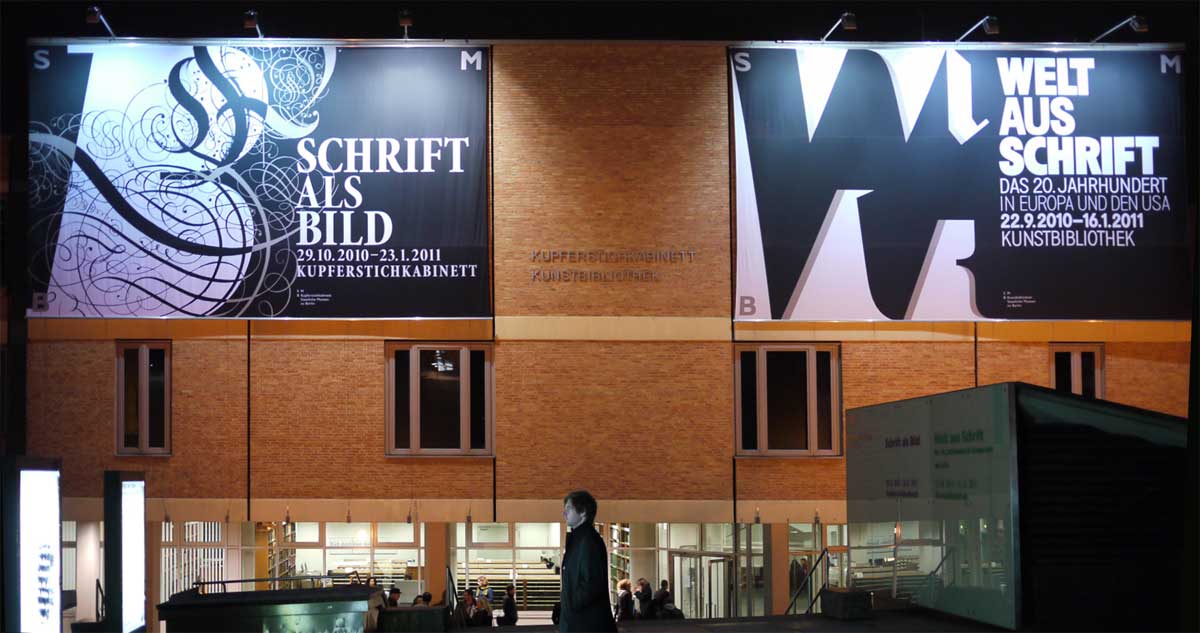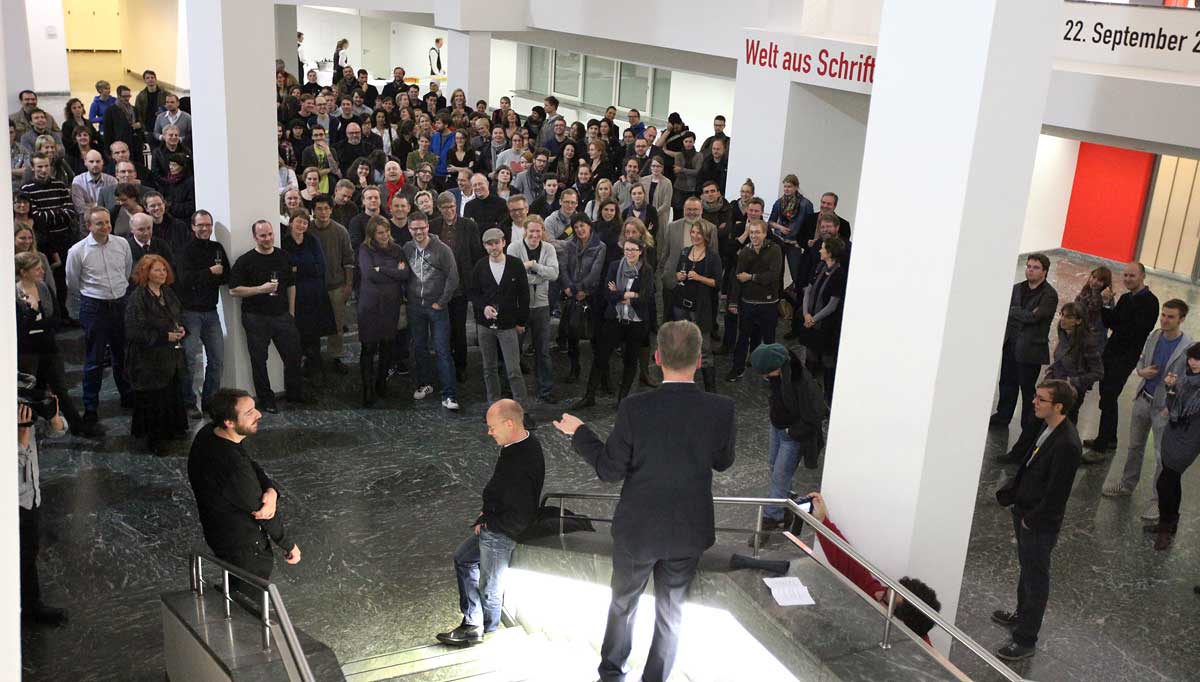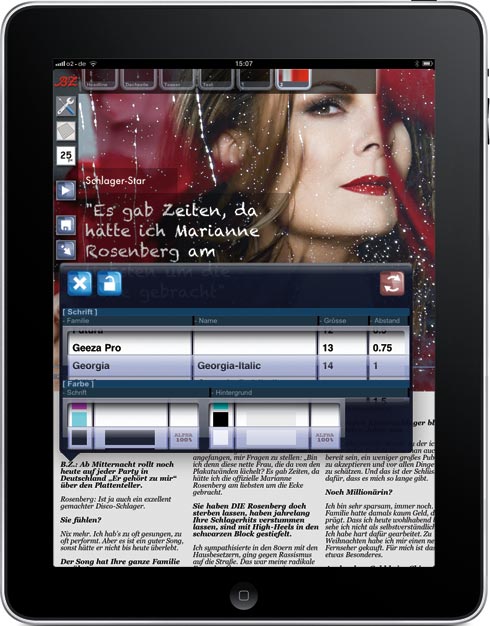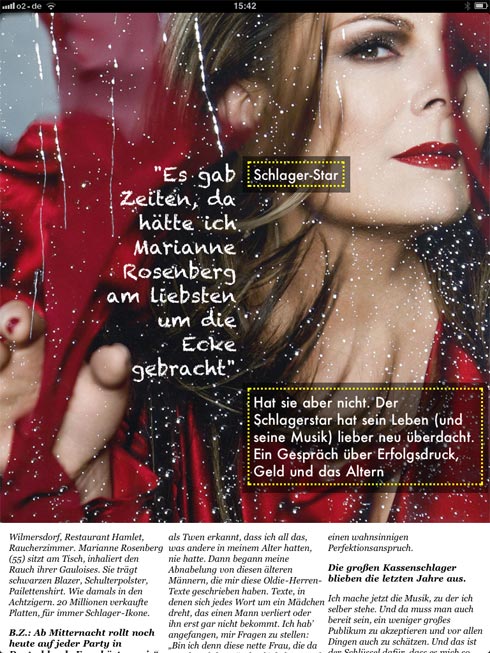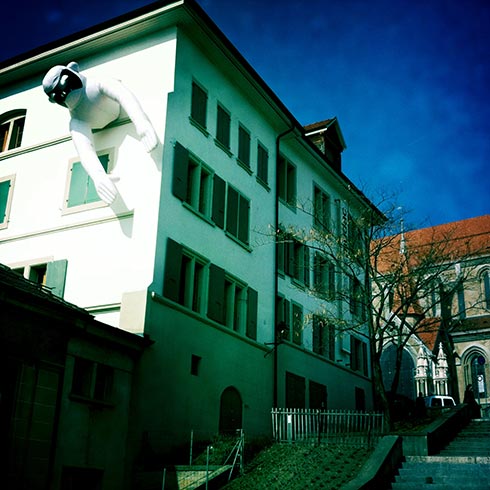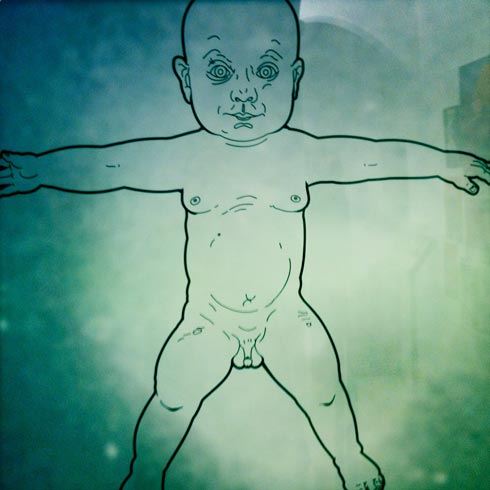
Seit 15 Jahren arbeitet der holländische Designer Diederik Corvers, Sprecher auf der TYPO Berlin 2010, mit Schrift und Typografie. In seinen kommerziellen und freien Arbeiten spielt die Textbehandlung stets eine zentrale Rolle. Corvers setzt meist eigene Fonts ein. Er produziert Bücher, Poster und CIs für verschiedene Auftraggeber in der Kulturszene. Seine autonomen Projekte finden sich im öffentlichen Raum, also da, wo Größe eher in Metern als in Punkt gemessen wird.
Heute schreibt er mir, dass seine wichtigste Schöpfung, die Schriftfamilie Ogentroost kurz vor der Fertigstellung steht. In einem reichlich bebilderten Interview mit der belgischen Designerin Veerle Pieters (Veerle’s Blog) erläutert er, warum die Arbeit an der Familie aufwändig war und so lange gedauert hat. Ein interessanter Blick hinter die Kulissen einer Schriftschöpfung: Ogentroost typeface
Im Zentrum von Lausanne, zu Füßen der Kathedrale Notre-Dame, liegt das angesagte Museum für Design und angewandte zeitgenössische Kunst, abgekürzt Mudac. Es versteht sich als Brückenbauer zwischen Kunstformen, die im traditionellen Verständnis etwas weiter auseinander liegen. Nirgendwo anders scheint eine Stefan-Sagmeister-Ausstellung besser hinzupassen, als an diesen Ort. Heute Abend war Vernissage.
Baby-boy: Das Leitmotiv der aktuellen Sagmeister-Retrospektive in Lausanne und die Hauptfigur des Ausstellungsplakats: die Baby-Karikatur
Aufgeblasener Affe: Gleich neben der Kathedrale, auf dem Stadthügel, erhebt sich die klare Silhouette des Mudac … doch in diesen Wochen ist etwas anders …
Ich wollte es erst nicht glauben, als ich bei der Recherche für meinen Beitrag über das neue Digitalmagazin »Berliner Zeiten« erfuhr, dass die gesamte Gestaltung des B.Z.-Ablegers auf iPads stattgefunden haben soll. Dann lud mich der Chefredakteur der B.Z. Peter Huth auch noch per Fontblog-Kommentar zum Testen der App ein. Das ließ ich mir nicht zweimal sagen. Einen Tag später saß ich in seinem Büro am Kurfürstendamm und ließ mir die Software auf mein iPad spielen. Eben habe ich – in 20 Minuten – meine erste Magazinseite damit gebaut, ein Interview mit dem Idol meiner Jugend, Marianne Rosenberg (Abbildung ganz unten).
Es dauerte zunächst etwas, bis ich mich in die Logik der App eingefummelt hatte. Das liegt schlicht daran, dass sie für die interne Nutzung der B.Z.-Redaktion entwickelt wurde und nicht für die breiten Bedürfnisse einer Editorial-Design-Kundschaft. Das beginnt bereits bei der Bereitstellung der Inhalte. Da sich die monatlich erscheinende Berliner Zeiten aus dem bereits veröffentlichten Material der Mutterzeitung bedient, liegt das Material für eine Geschichte – fix und fertig aufbereitet und nicht editierbar – auf dem Server. Die Bausteine werden in einer Palette am Kopf der Arbeitsfläche angeboten, von links nach rechts sind das für meine Story die Headline, Dachzeile, Teaser, der Text und 2 Fotos. Am linken Bildschirmrand befindet sich die Werkzeugleiste mit den Funktionen: Struktur (eine Mischung aus Inhaltsverzeichnis und Materialsammlung), Raster, magnetische Positionierung (1 px, 5 px, 10 px, 25 pxund 50 px), Wiedergabe (vergleichbar mit Seite ansehen), Speichern und Laden. Beide Paletten stoßen in der linken oberen Ecke zusammen, ein Fingertipp auf das verbindende B.Z.-Logo in der Ecke fährt die Paletten ein oder aus.
Meine erste Amtshandlung ist das Aufrufen der hoch aufgelösten Aufmacherabbildung, Marianne Rosenberg mit kirschroten Lippen in frivoler Pose hinter eine regennassen Glasscheibe. Das Foto lässt sich beliebig mit Kneifgesten vergrößern, verkleinern und beschneiden. Ein doppelter Fingertipp öffnet ein Bildbearbeitungswerkzeug, mit dem sich das Foto farbig hinterlegen und in 10-%-Schritten transparent darüber kopieren ließe. Ich verzichte auf solche Spielereien, die ich gerne erfahrenen Layoutern überlasse.
Danach die Headline, in diesem Fall ein Zitat. Sie öffnet sich in einem skalierbaren Fenster, und umbricht automatisch beim Verändern der Fenstergröße. Ein doppelter Fingerzeig auf den Text öffnet ein Bearbeitungswerkzeug, das weitaus mehr Optionen anbietet als die Bildbearbeitung, darunter Schriftart, -größe, Zeilenabstand, Ausrichtung, Spaltenzahl und -breite, Rahmen, Rahmenfarbe … und natürlich lässt sich auch die Schrift mit Farbe und Transparenzen inszenieren. Eigens für das Lesen am iPad gibt es noch die beiden Einstellungen »Textbox hat exakt die angelegte Größe« und »Textbox passt sich im Live-View automatisch an«.
Nach der Headline platziere ich die Dachzeile und den Teaser, denen ich den gleichen Stil zuweise. Nun noch ein bisschen Hin- und Herschieben, und fertig ist die Magazinseite … im Rahmen meiner bescheidenen Möglichkeiten, ich habe weder Design studiert, noch praktiziert. Ich kann sie jetzt auf den Server der B.Z. laden, oder lokal auf meinem iPad.
Das Faszinierende an dieser Methode der iPad-Magazingestaltung ist die 100-prozentige Wysiwyg-Bearbeitung (What you see is what you get). Ich sehe beim Aufbau der Seite, beim Festlegen der Schriftgröße immer exakt das, was die Leser später auf ihrem iPad sehen werden. Weder werden Bilder umgerechnet, noch Texte skaliert, neu gerendert und/oder interpoliert. Das Ergebnis der B.Z.-Layout-App sind kristallklare Seiten, die mit den im iPad eingebauten Schriften arbeiten und am Ende ein schlankes Magazin ergeben, das rund 20 MB wiegt.
Entwickelt wurde die native Layout-App von Markus Glasmeier. Er hat sich inzwischen selbstständig gemacht und arbeitet gerade unter dem Namen eXPublica an einem neuartigen Redaktionssystem, mit dem man auf iOs- und Android-basierten Geräten redaktionelle Inhalte publizieren kann. Wie leistungsfähig das B.Z.-Programm bereits ist, beweist allein der Umstand der Entstehung der Erstausgabe von Berliner Zeiten: Die B.Z.-Chefin vom Dienst Irina Praß soll sie angeblich an einem Urlaubswochenende auf Sylt mit ihrem iPad zusammengebaut haben.
Eigentlich sollte die lang erwartete iPad-Tageszeitung »The Daily« Mitte Januar an den Start gehen. Im Dezember hofften die Apple-Jünger noch, dass Steve Jobs und der News-Corporation-Boss Rupert Murdoch ihr Vorzeigeprojekt gemeinsam vorstellen würden. Dann meldete sich zunächst der Apple-Gründer krank, anschließend musste seine Company das Abo-Modell für den Bezug von The Daily über den App-Store neu programmieren.
Florian Hardwig (links) und Erik Spiekermann führten jeweils 150 Besucher durch die Ausstellung, ausgestattet mit Funkmikrofon und kabelloser Verstärkerbox
FontShop-Vorstand Jürgen Siebert und die beiden Schriftexperten begrüßen die Besucher im Foyer der Kunstbibliothek und erläutern, was in den kommenden 2 Stunden passieren wird